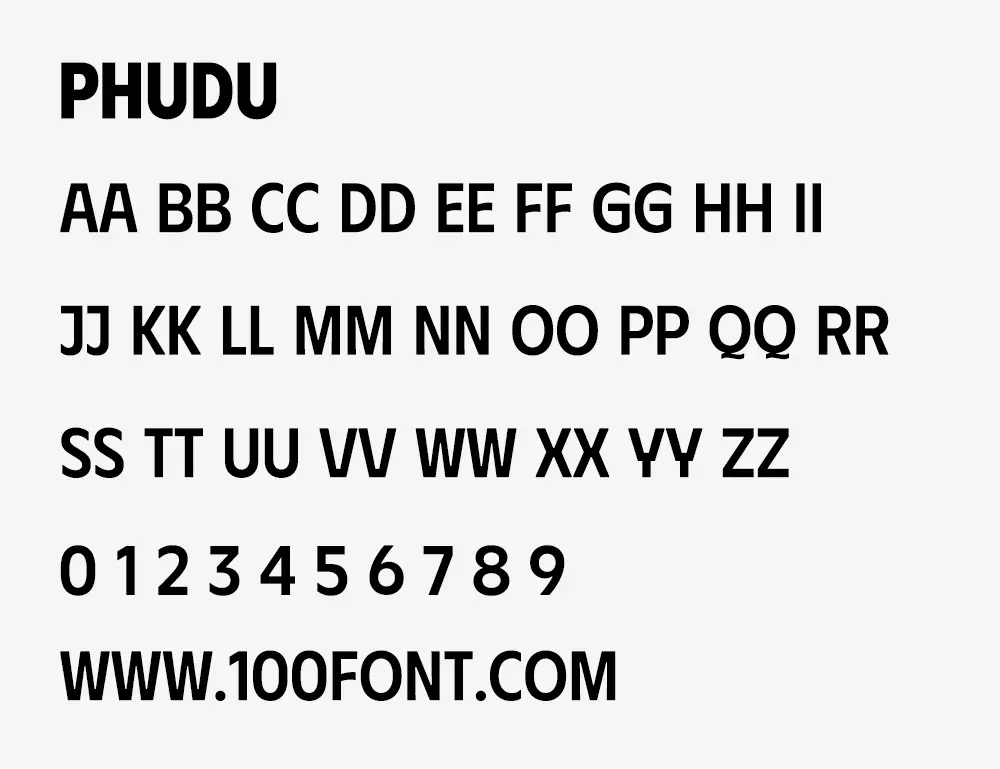
DT Phudu是一種無襯線字體,靈感來自過去越南的手寫廣告牌。它由從淺色到黑色的5個權重組成,與其他輕量級窄字體相比,它越輕,就越擴展,以提高可讀性。有些細節是尖端的,並沒有為此目的而變得尖銳。DT Phudu有相同的大寫和小寫,只使用全大寫的信息顯示,就像我們越南的廣告牌風格。
我為甚麼要做這種字體?在學習和製作字體的過程中,我一直在思考是甚麼造就了越南字體。如果我們回到過去,我們可以在廣告牌商店看到我們的字體風格,當時藝術家們改編了拉丁字體,然後根據他們的風格添加了標記。其中,大多數都是無襯線的大寫字母,用作描述,有時也用作商店名稱本身。為了製作一種新的易讀易用的字體,我將上面故事中的一些研究與字母混合在一起。我不想只是復興這些類型,我想改進它們,這樣它們就可以適應現代風格,但仍然有“越南人”的靈魂。字體命名為DT Phudu(phục dựng)-越南語中的“復興”,具有永恆的含義(與名稱相反,它可以讀作“phúdu”-短暫)。
DT Phudu is a display sans-serif typeface inspired by Vietnamese hand-lettering billboards in the old days. It consists of 5 weights from Light to Black, and the lighter it gets, the extended it becomes, for readability compared to other lightweight narrow typefaces. Some details are cutting-edge and not sharpened for this purpose too. DT Phudu has the same upper and lower-case, with the message of using only ALLCAPS for display purposes just like our Vietnamese billboard styles.
Why I made this typeface? In the process of learning and crafting types, I have always thought about what makes a Vietnamese typeface. If we rewind to the past, we can see our lettering styles on the billboard stores, when the artists adapted Latin typefaces and then added marks based on their styles. Among those, there were mostly all-caps sans-serif types played as descriptions or sometimes the store's names themself. To make a new easy to read and easy-to-get typeface, I mixed some of the research from the story above with letters. I don't want to just revive the types, I want to improve them, so they can fit the modern-day styles but still have "Vietnamese" souls in them. The typeface was named DT Phudu (phục dựng) - "revival" in Vietnamese, and has a meaning of timeless (quite the opposite of the name when it can be read as "phù du" - ephemeral).